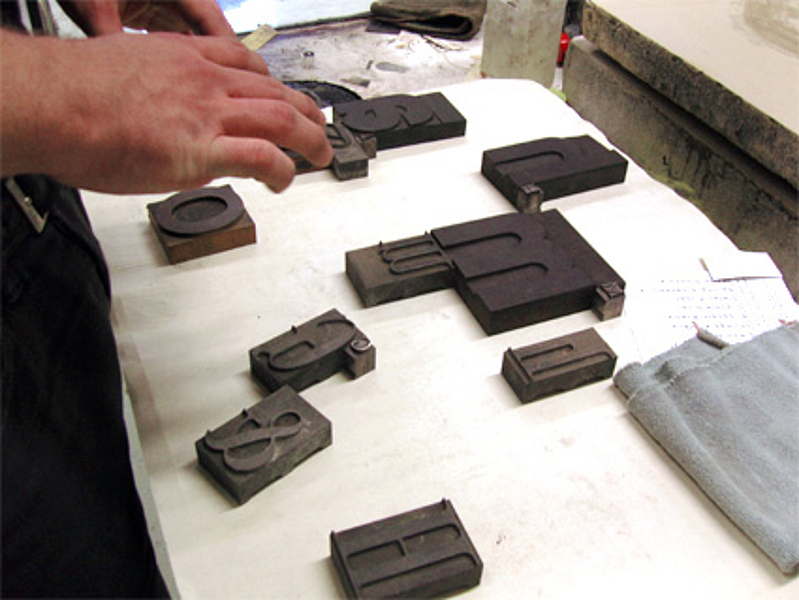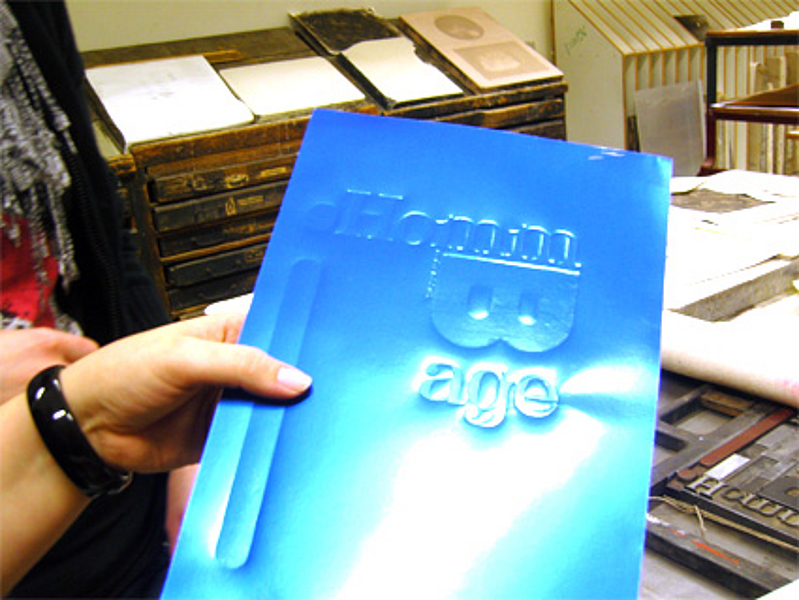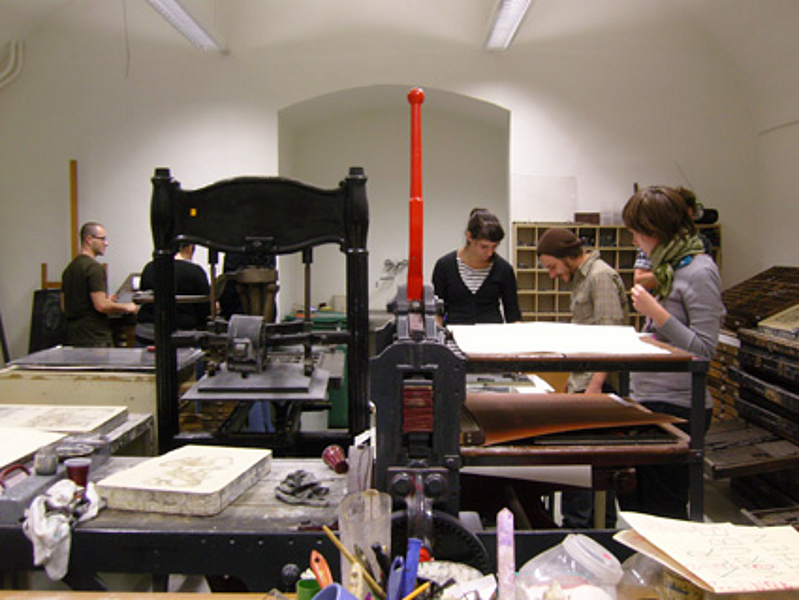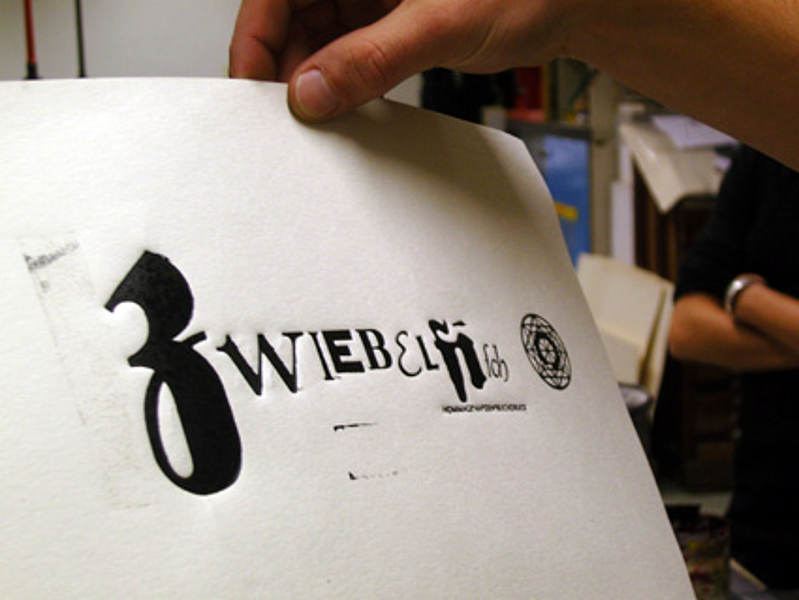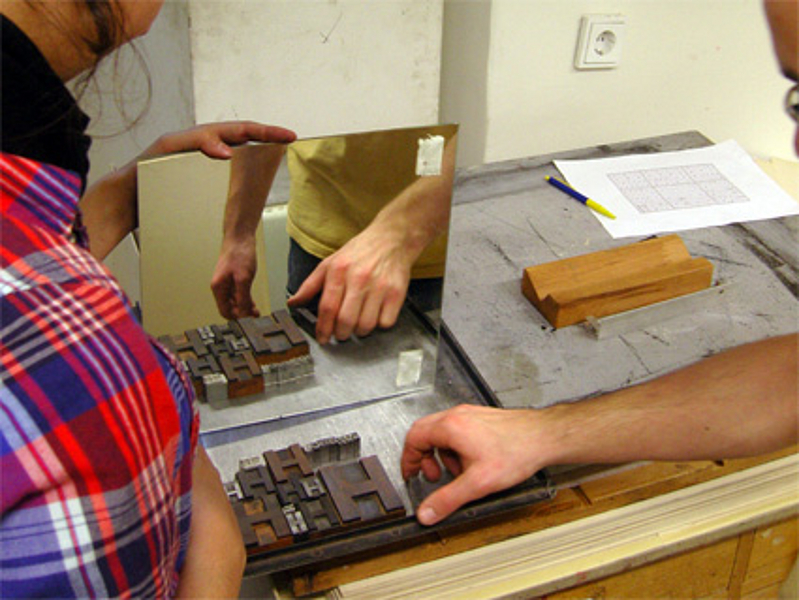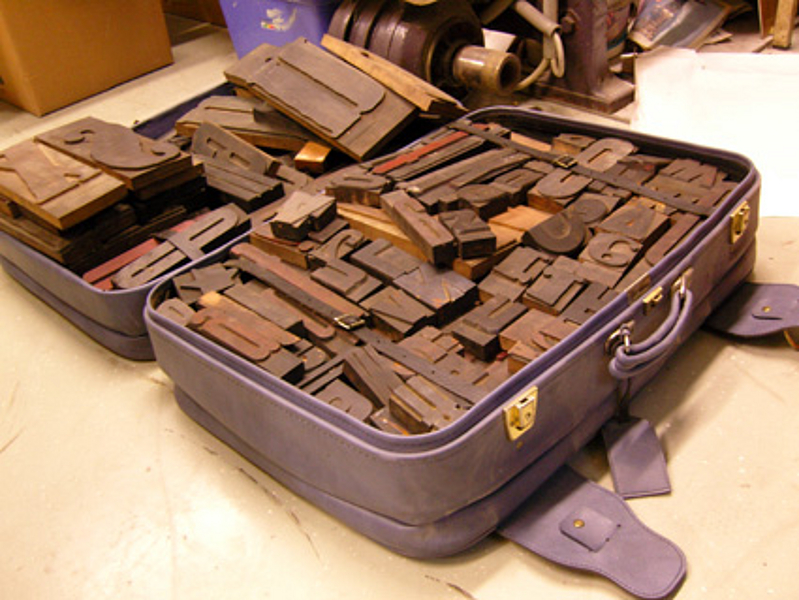
Experimentelle Typografie
Workshop zum Thema "Buchdruck"
WS 2009
Masterstudium Visuelle Kommunikation
Im Rahmen der Lehrveranstaltung Experimentelle Typografie (WS 2009) fand ein Workshop zum Thema "Buchdruck" statt. Experimentiert wurde mit Bleisatz, Holzbuchstaben und Handpresse fernab vom typografischen Regelwerk. – Entstanden sind freie Arbeiten als eine Hommage an den Buchdruck.